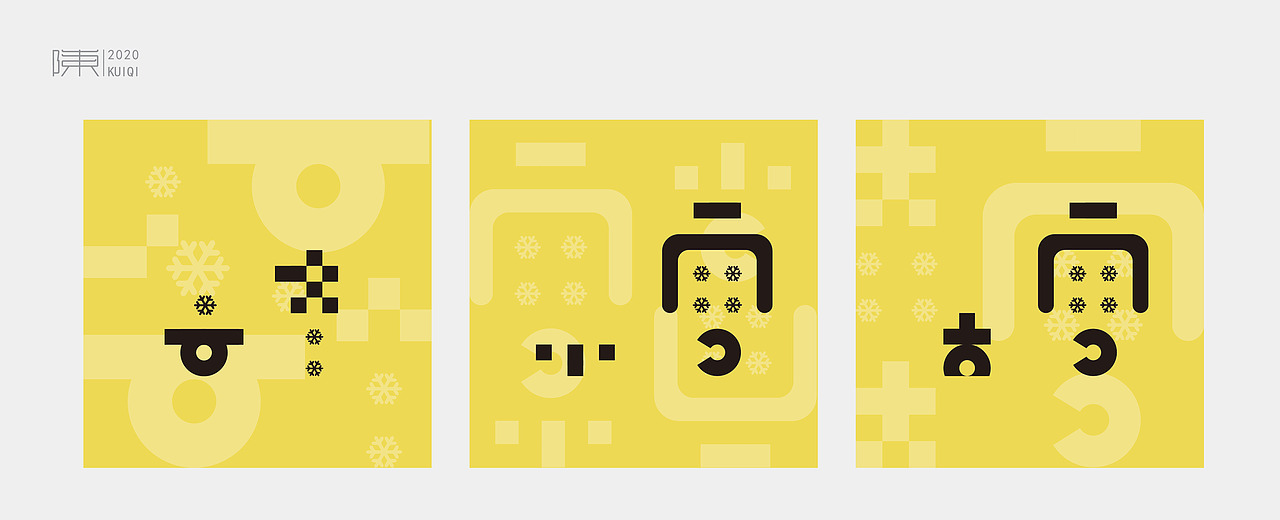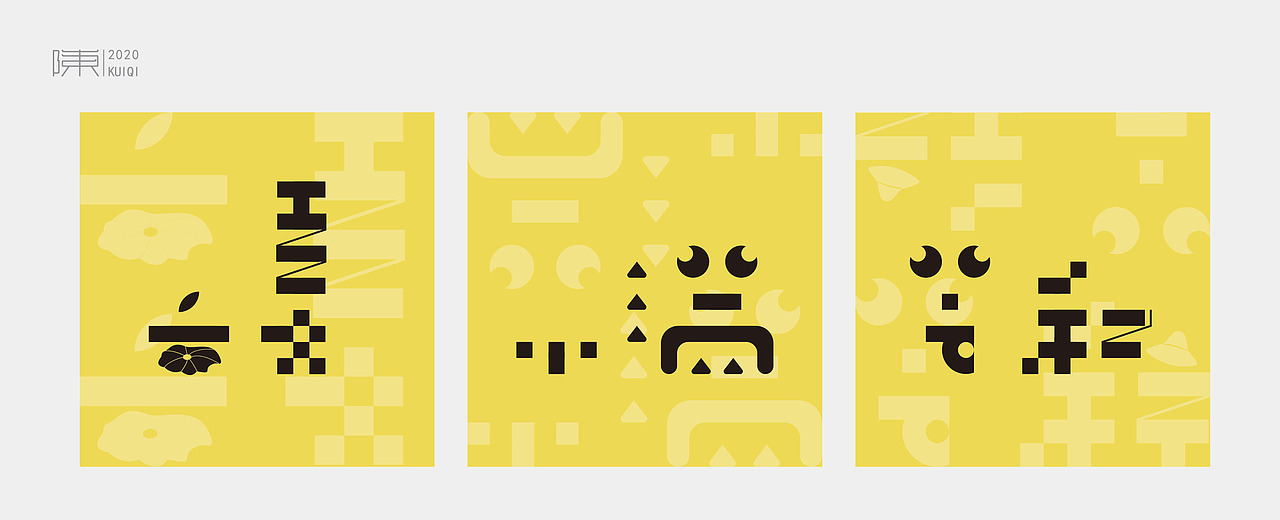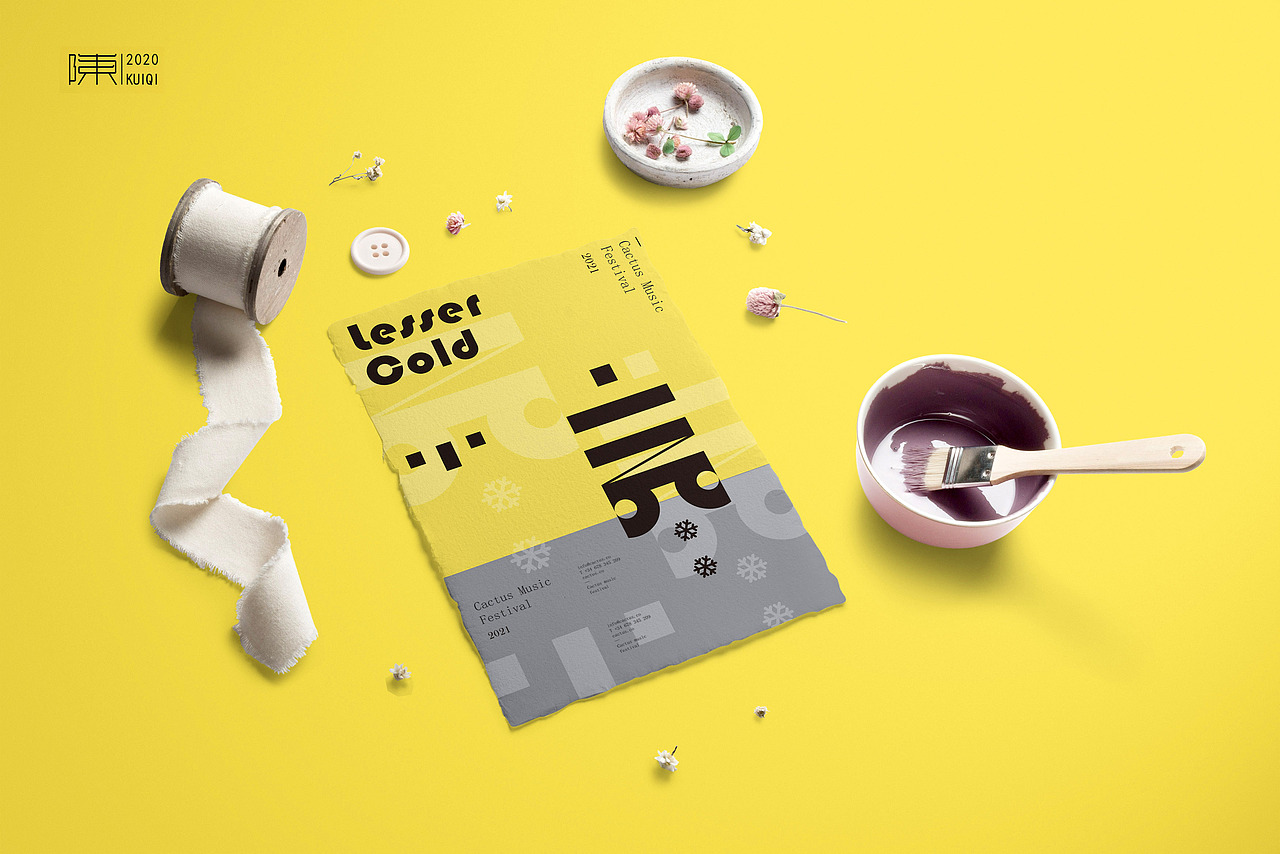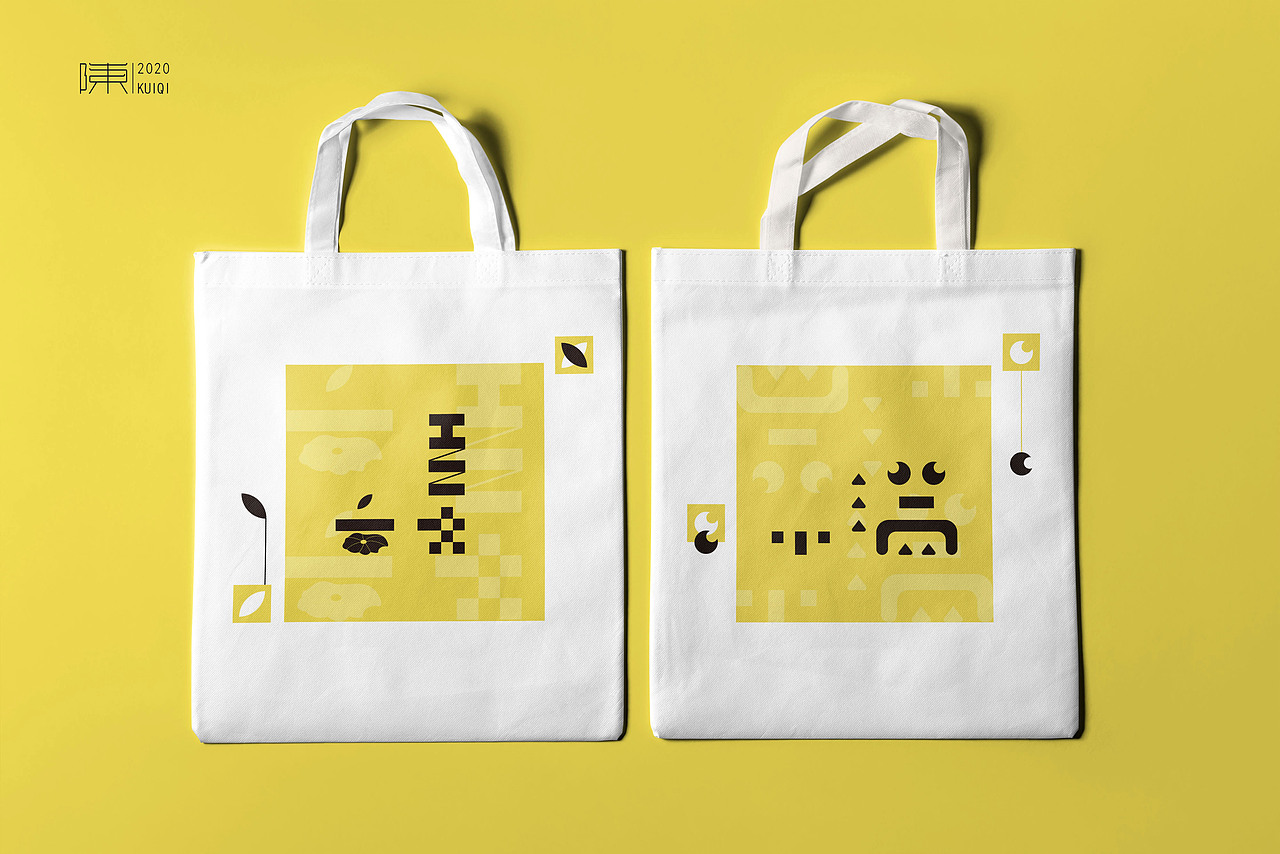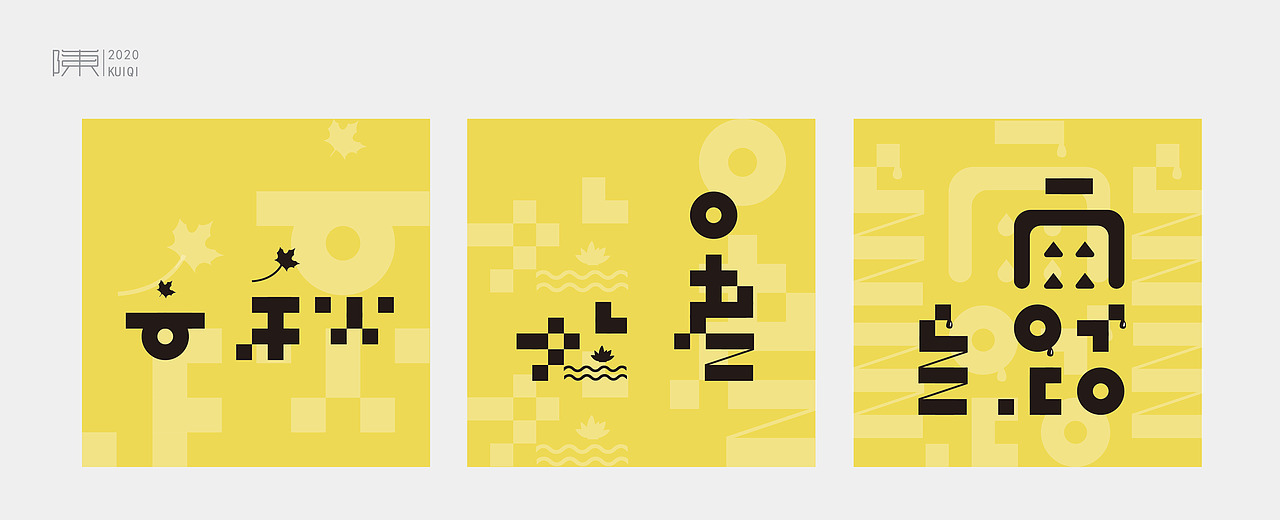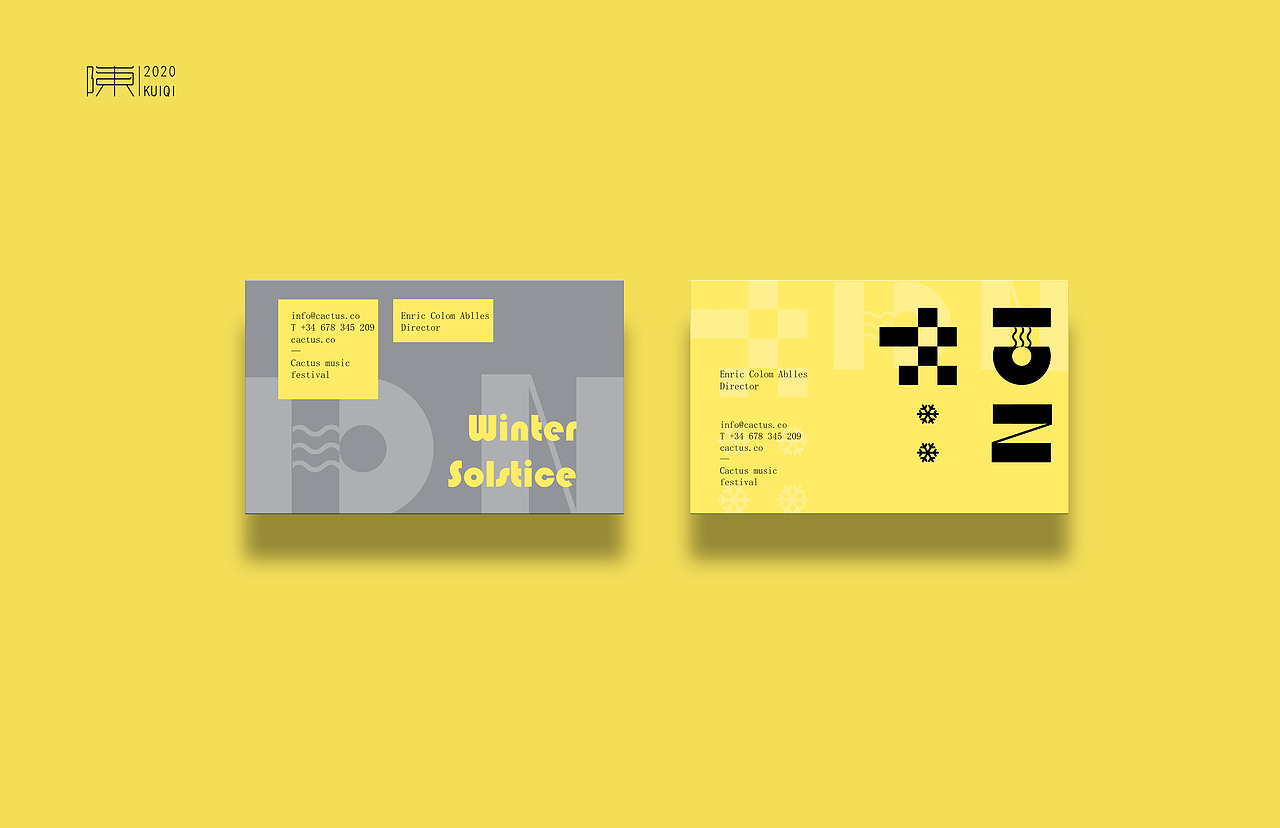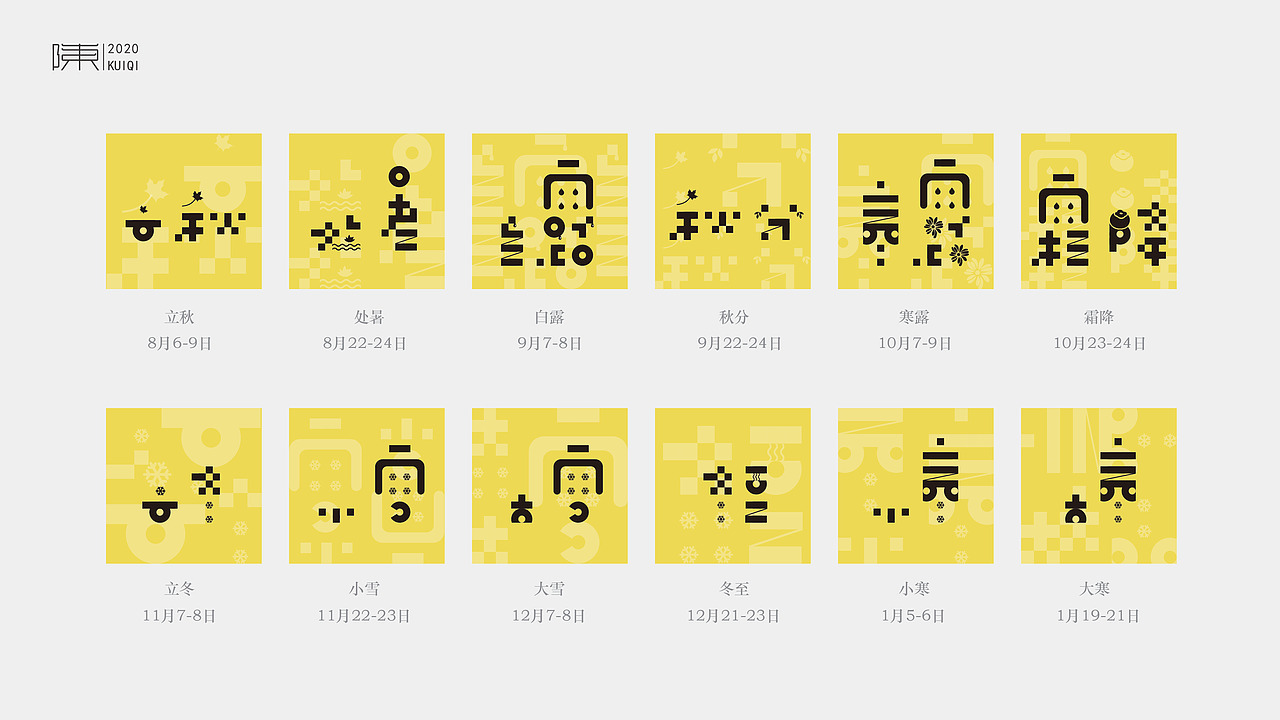
字体 | 二十四节气
国际色彩权威机构Pantone发布了2021年度流行色
极致灰(PANTONE 17-5104 Ultimate Gray)
亮丽黄(PANTONE 13-0647 Illuminating)
Pantone的官方解释是
“这两个独立的色彩突显不同的元素如何在一起支持彼此,最能表达Pantone 2021年度代表色的精神。实用又稳固,同时温暖又乐观,二者是力量与正向的结合。这个色彩故事将深思熟虑的深层感受与阳光友善的希望浓缩在一起,为我们带来韧性与希望。我们需要感受到鼓舞与振奋,这是人类心灵的基本要素。”
2020年好像经历了很多
又好像一眨眼就没了
希望2021年祛除一切坏运气吧
借此做了一组二十四节气的字体设计
以此来迎接2021新的一年
希望每个节气都能充满活力与生机
使用了大面积的亮丽黄
小面积及低饱和度极致灰